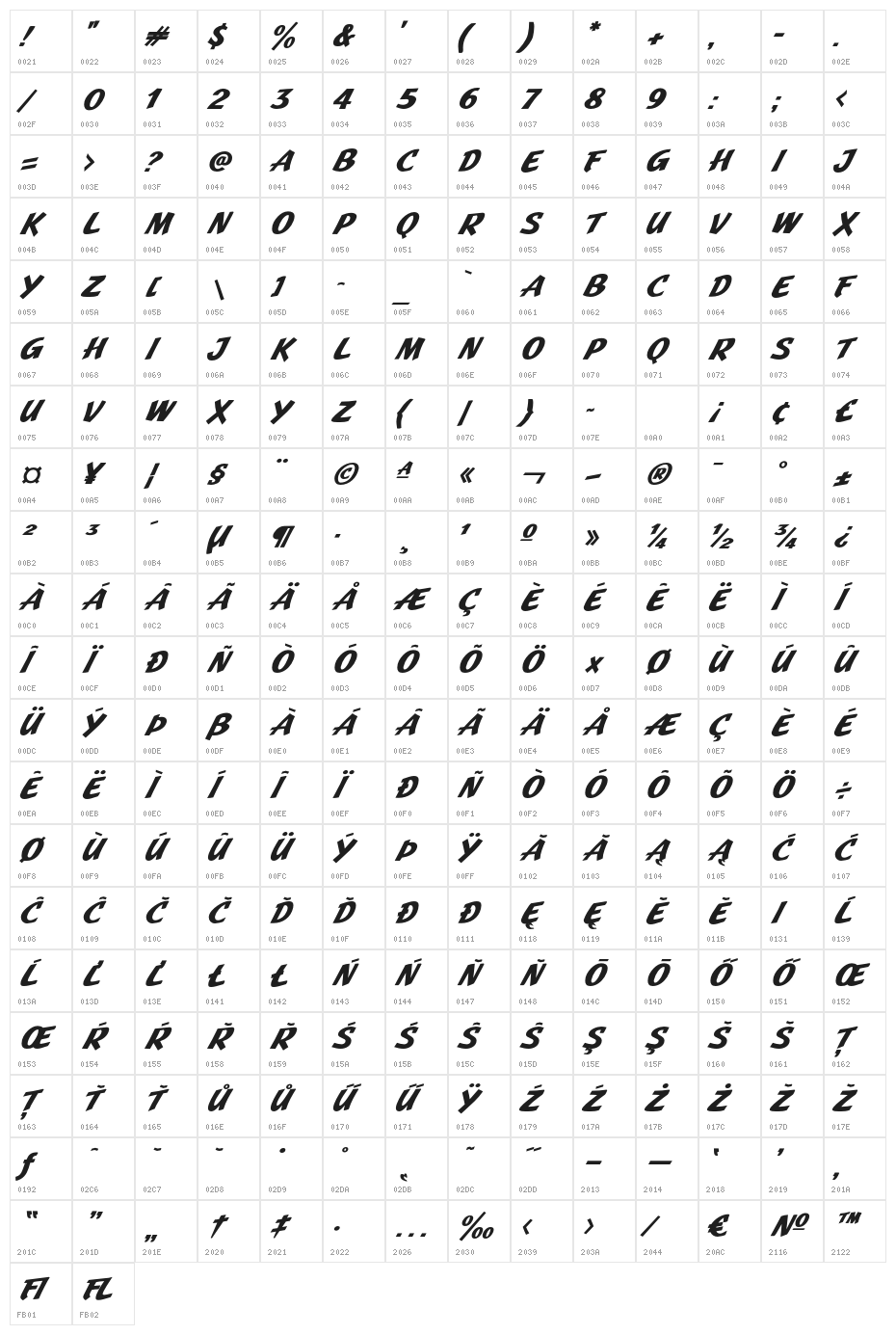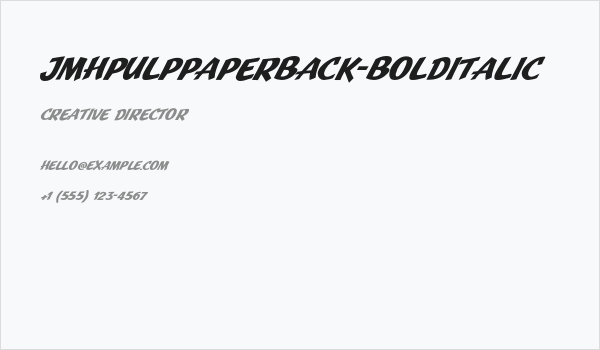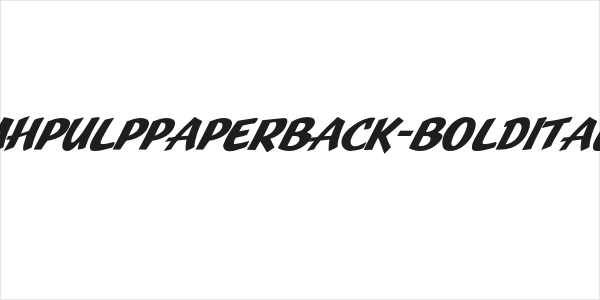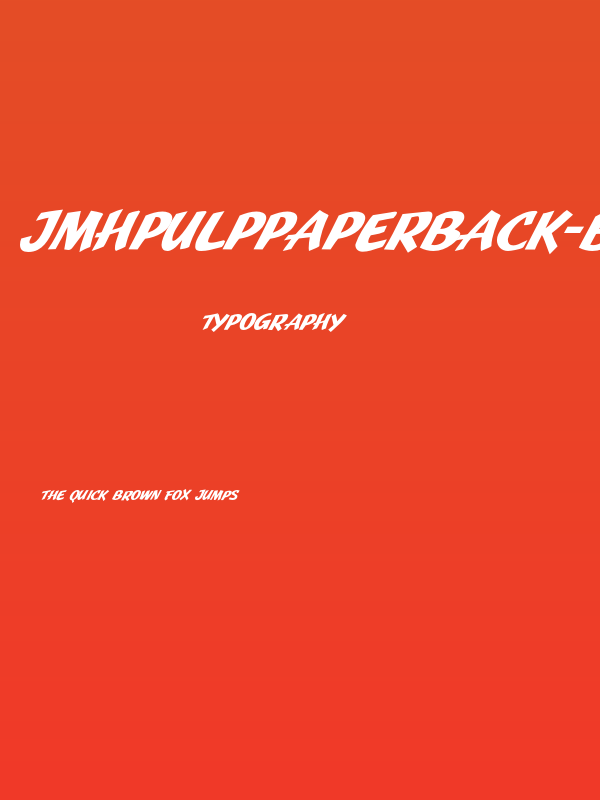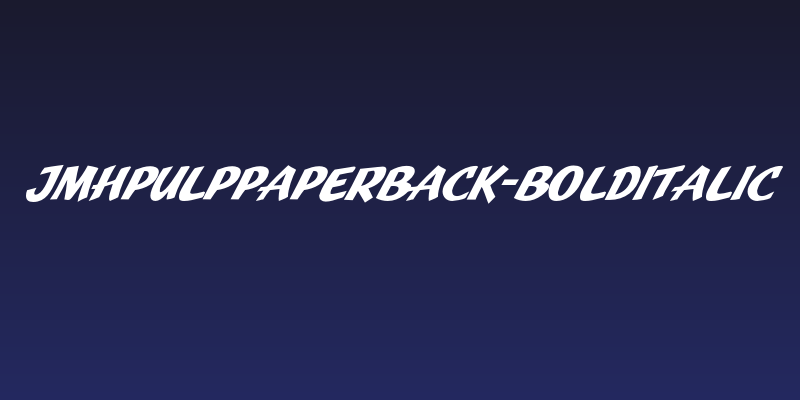
JMHPulpPaperback-BoldItalic Font
| Progetti proposti | Ideal for book covers, posters, and branding materials that require a bold and striking appearance. |